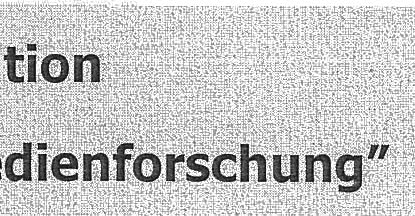
Was für ein Schriftsatz ist das?
"Gänsefüsschen" anders aus...noch ne Idee?
Und wo liegen die markanten Unterschiede zwischen Tahoma und Verdana außer im Zeichenabstand?